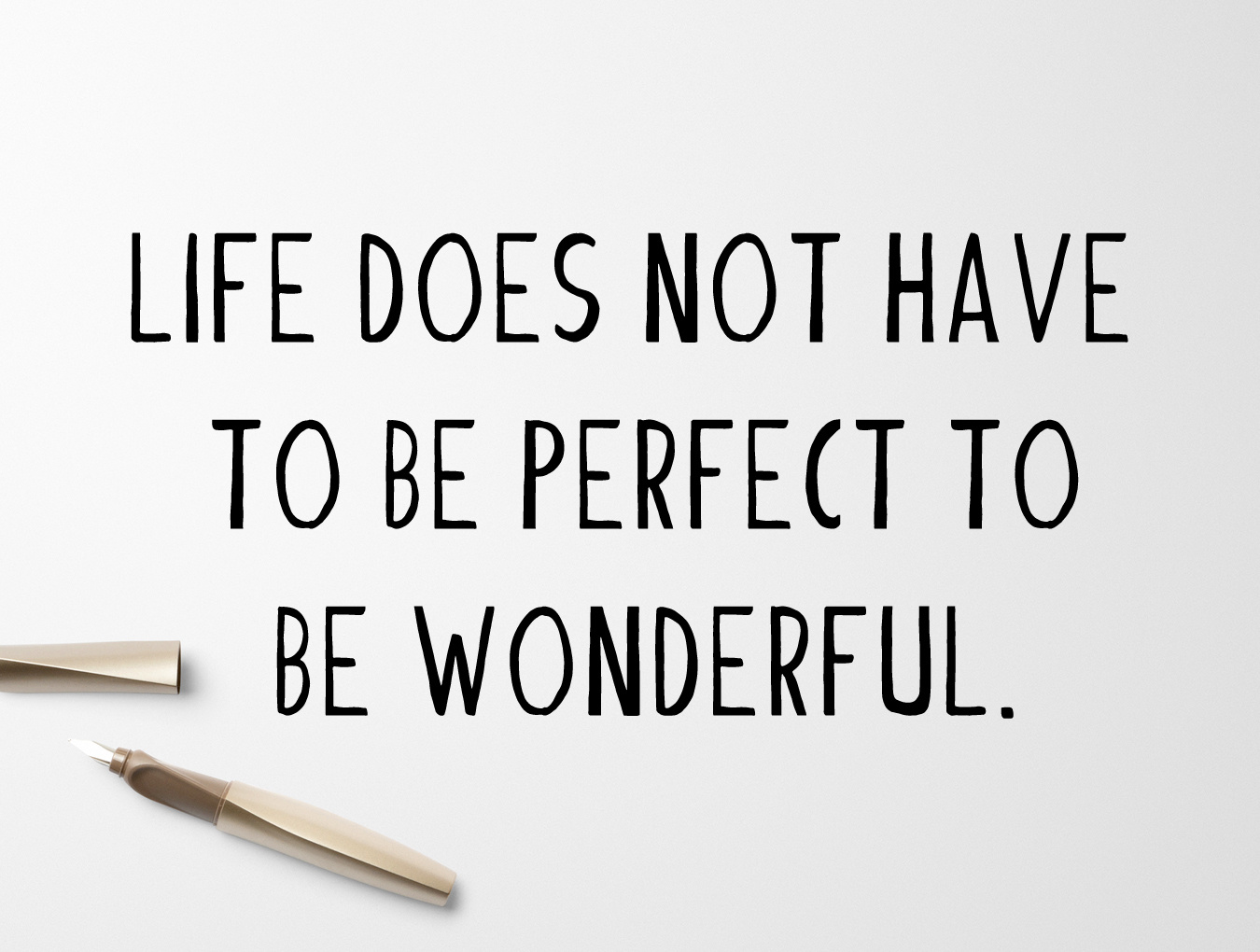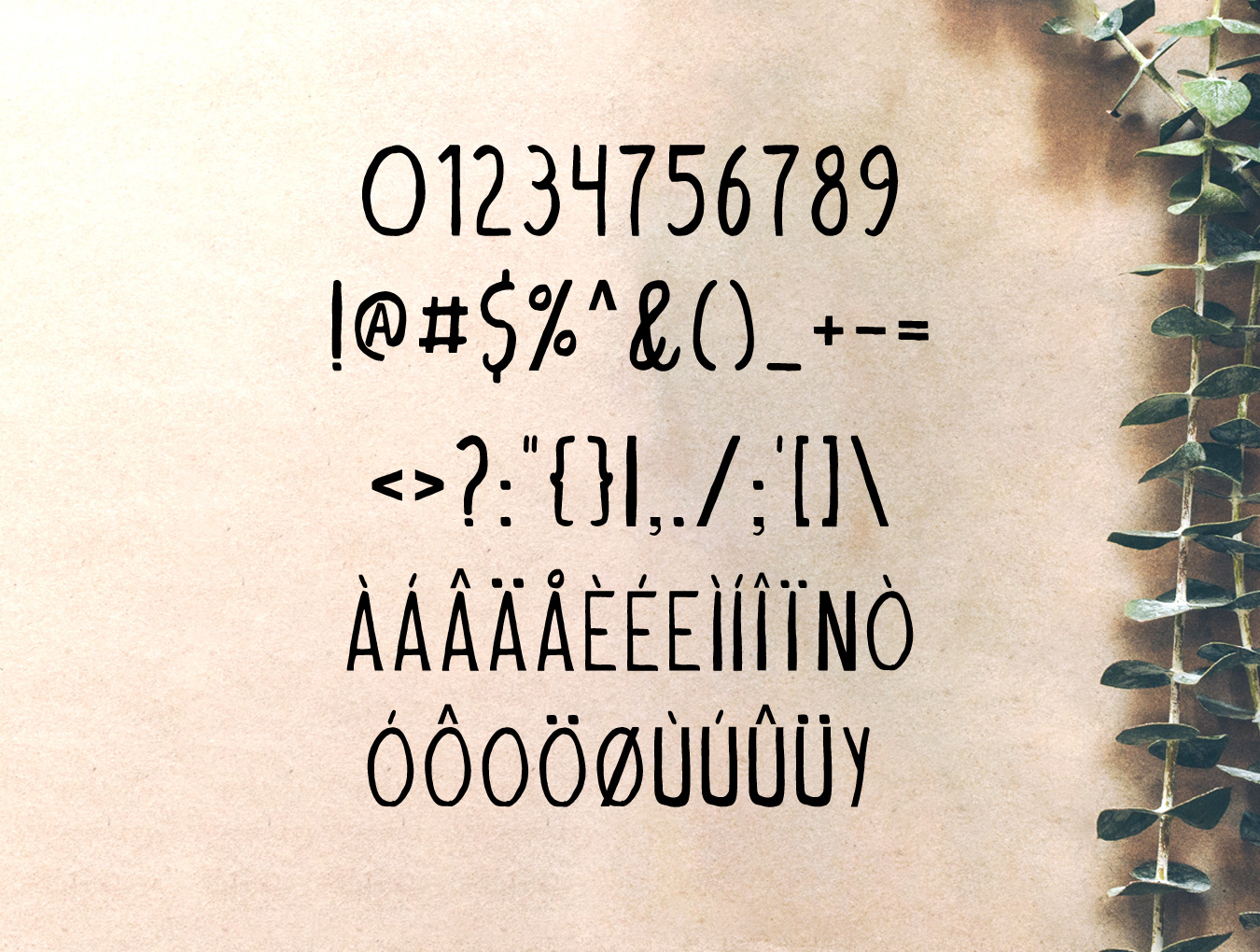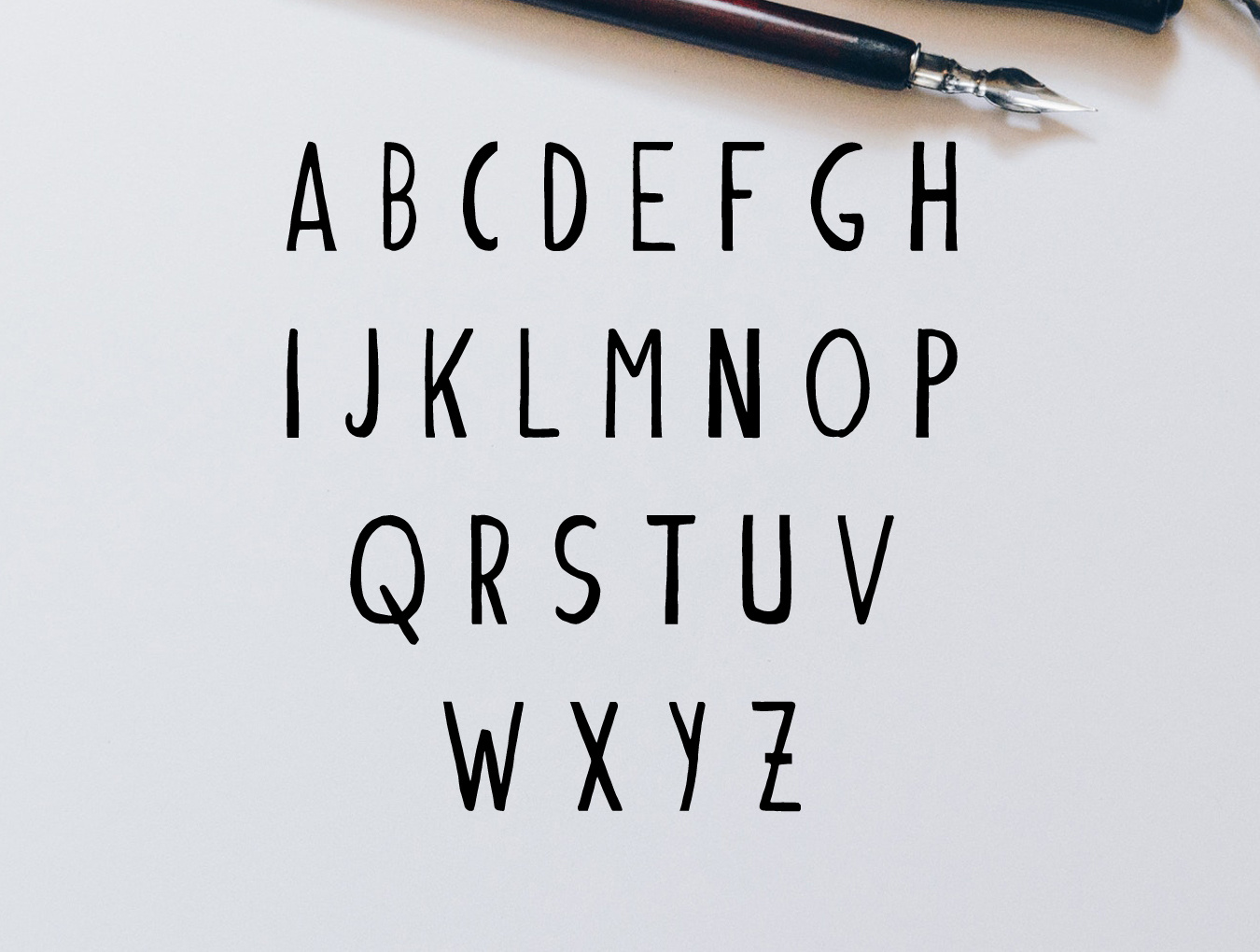
Talissa A Handmade Font, Talissa A Handmade Font
Talissa手工制作的字体它是一个美妙的字体设计,具有独特,细致和手工制作的外观。它看起来令人印象深刻的品牌,网站,设计,标题,横幅,海报,印刷品,T恤,标志,杂志,促销产品,平面广告,模板等。如果你看起来华丽的所有帽子宽大的间距想要尝试一种优雅的外观,或者用大写字母和小写字母来表现完美永恒的东西。